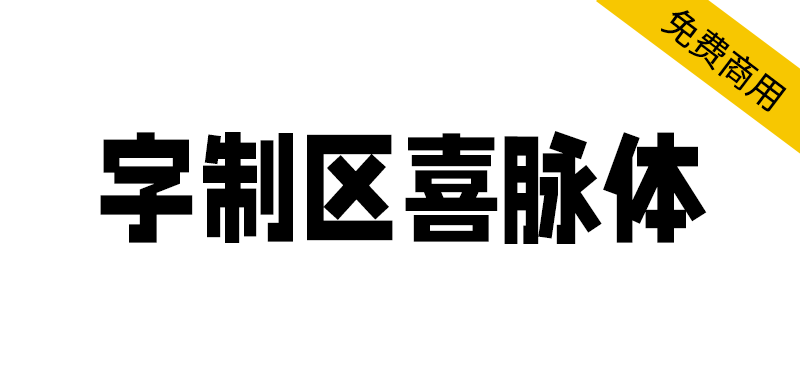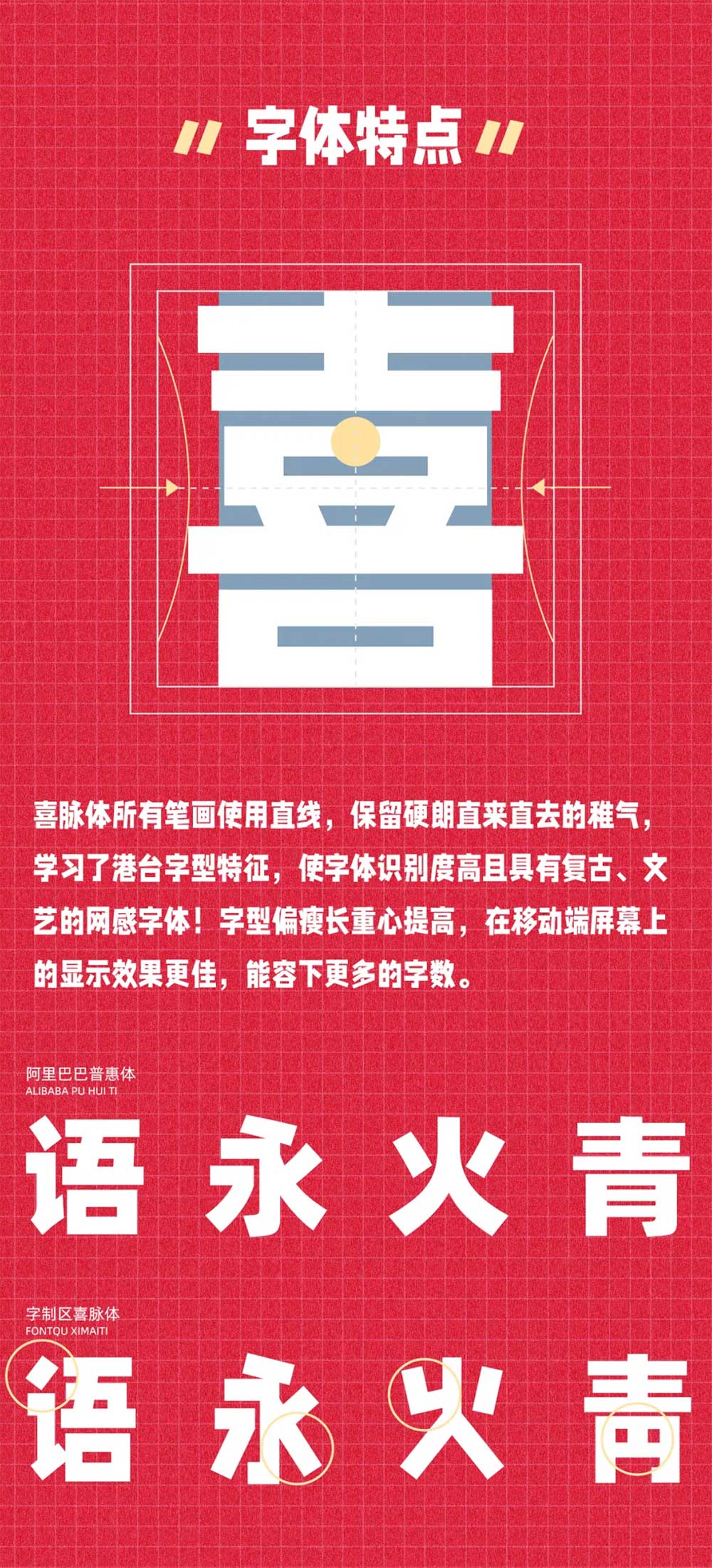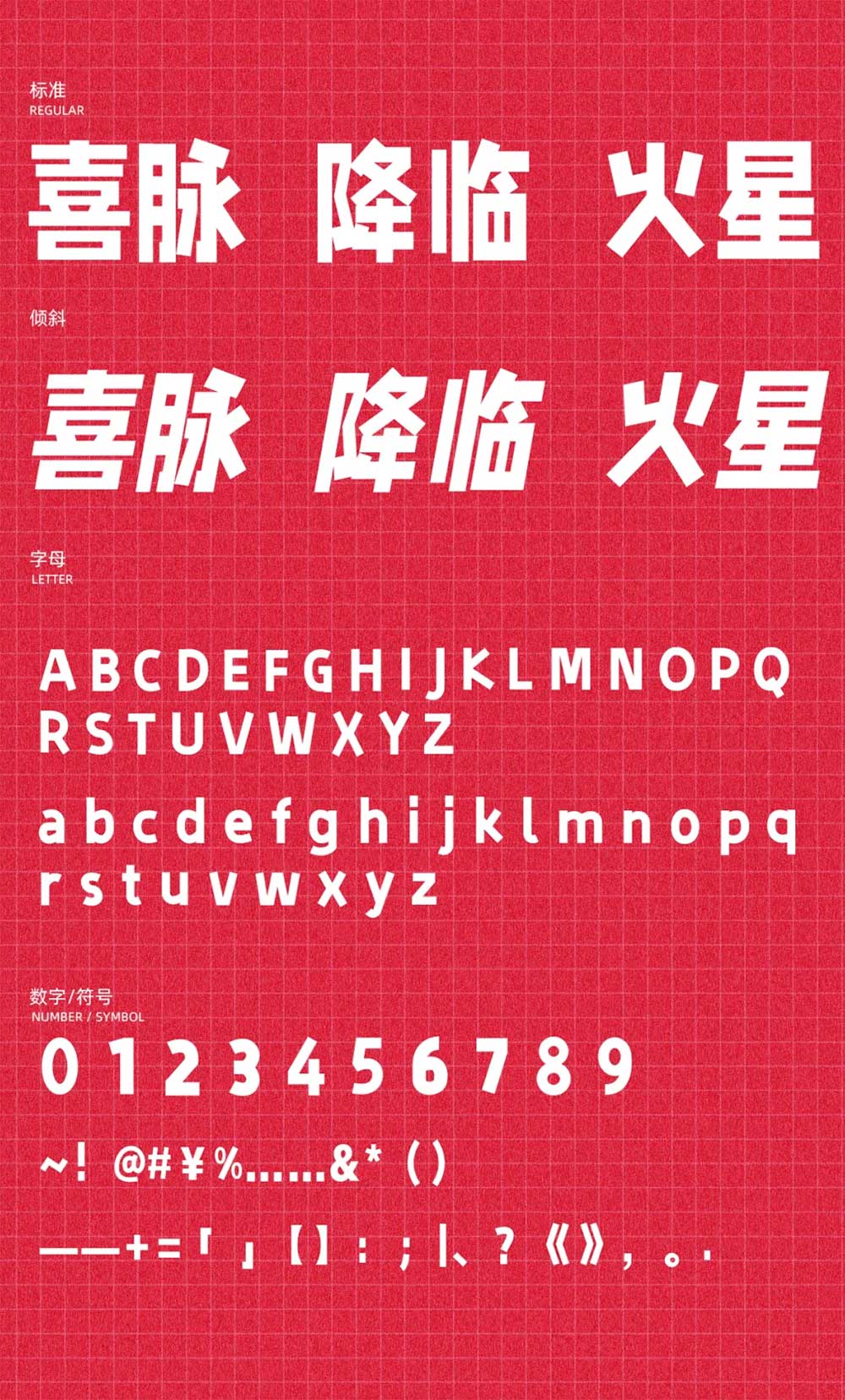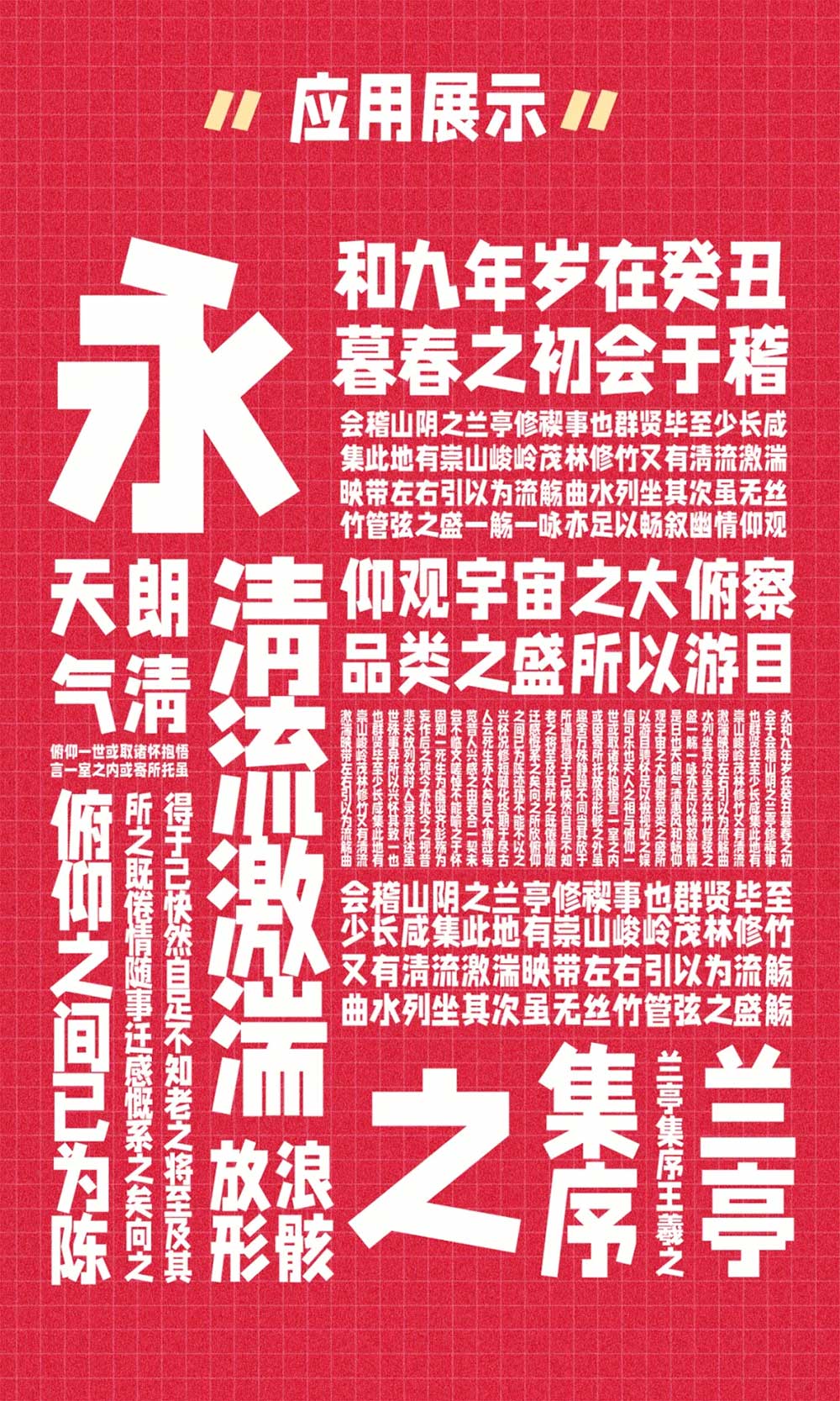
2020年,有6个人(肖维野纳、陈玲玲、林鸿雷、刘欢、李斌、钟诚)花了7个月的时间,做了一套公益字体,起因是大家一致的认为,人活着,总得在世上留下点什么.........
我国在5G技术、短视频行业上遥遥领先远胜他国,在这快速发展的节骨眼上,字体文化的发展却没有更上,创作者永远缺少一款合适手机屏幕的免费字体、缺少一款具有网感的免费综艺字体;所以我们想尽一点力,给咱们即将到来的30岁留下一点热血与喜爱!于是诞生了这款字体——字制区喜脉体
字制区喜脉体所有笔画使用直线,保留硬朗直来直去的雅气,学习了港台字型特征,使字体识别度高且具有复古、文艺的网感字体!字型偏瘦长重心提高,在移动端屏幕上的显示效果更佳,能容下更多的字数。
文字范围:简体中文收录《通用规范汉字表》一级字表、二级子表及一些额外增补字。西文收录BASIC LATIN(ASCII)及一些额外增补字,字符7090余字。